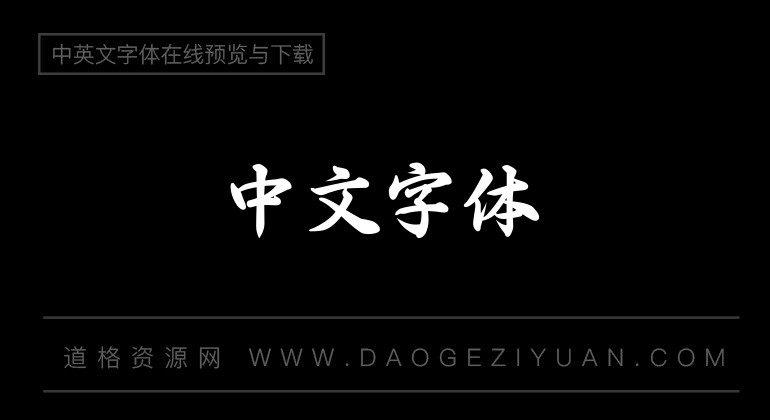
EPSON 太行書体B
? EPSON 太行書体B是一种日本传统的行书字体,它是由日本传统書法家太行書体的技法发展而来的。太行書体B的特点是字形比较粗犷,笔画比较厚实,线条粗细有致,形状简洁,具有良好的空间感和视觉效果。它可以用于报纸、杂志、书籍、海报、海报等印刷品的文字排版,也可以用于电脑设计和绘图。
EPSON 太行書体B是一款非常不错的手写艺术字体,具有很好的视觉感,适合于文化类的宣传设计、商业类品牌的广告和产品包装设计以及个性化文字排版等较多场景。